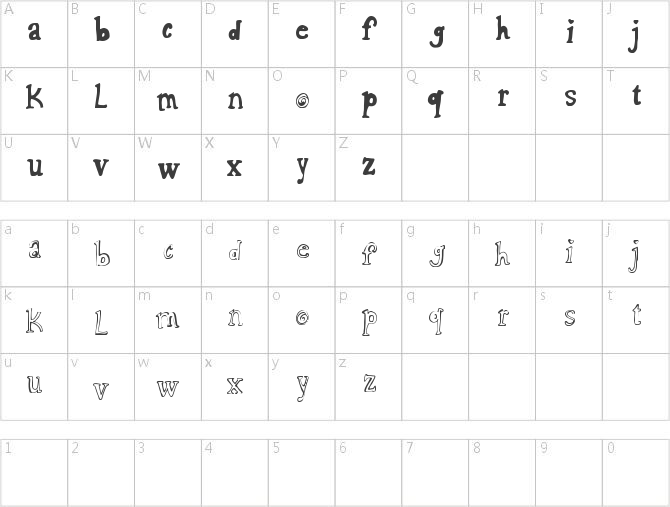
CF-Charlie-Regular
CF-Charlie-Regular介紹
CF-Charlie-Regular字體字庫(kù)是一款讓人賞心悅目、百看不厭的英文字體,適合各類廣告和產(chǎn)品包裝設(shè)計(jì)應(yīng)用,字體大小0.04MB,格式為ttf字體,上傳用戶是rose,作者/版權(quán)方為未知